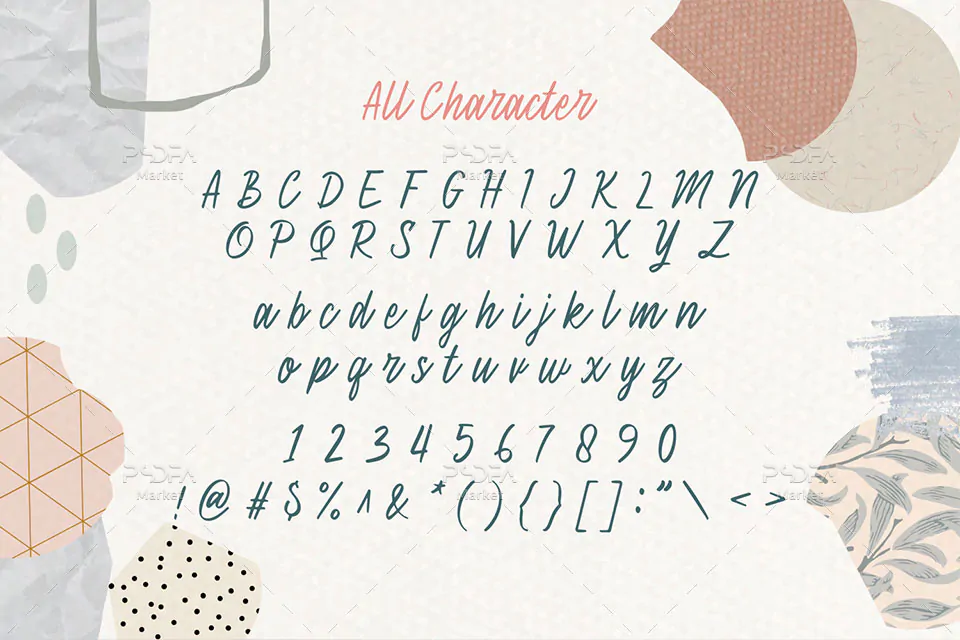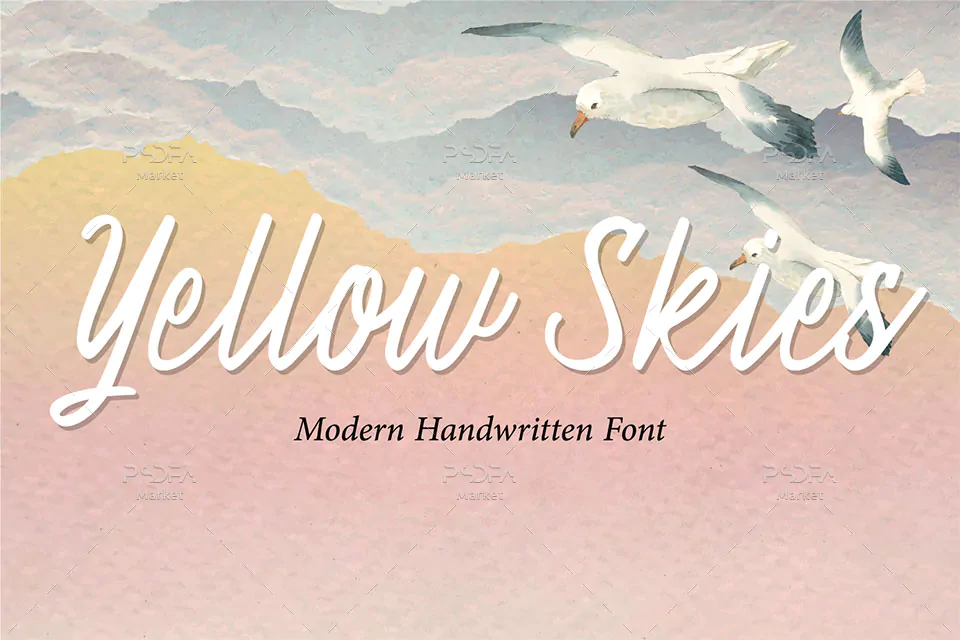
فونت انگلیسی پیوسته نویسی Yellow Skies یک قلم دستنویس انگلیسی است که میتوانید از آن در طرح و پروژههای گرافیکی مختلف استفاده کنید. فونت با فرمتهای ttf, otf در فایل محصول قرار دارد که با نصب آن در پوشه فونتهای سیستم میتوانید در تمام نرم افزارهای گرافیکی از این قلم زیبا استفاده کنید.
فونت Yellow Skies در وزن معمولی طراحی شده است و مناسب جهت استفاده در طرحهای گرافیکی مختلف همچون طراحی کارت ویزیت، بروشور، پوستر، تراکت، بسته بندی محصولات، ظروف یکبار مصرف، کارت تبریک، کارت پستال و … میباشد.